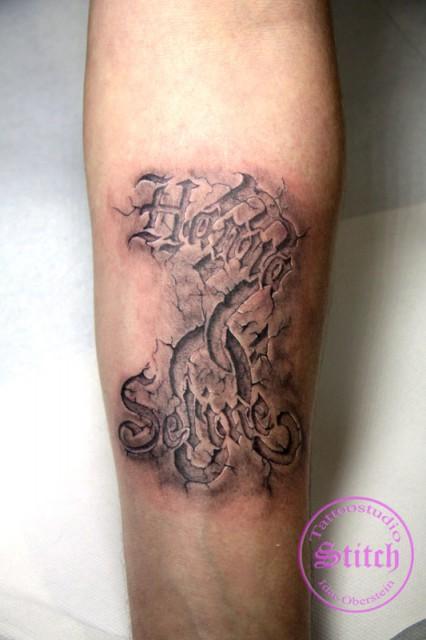
suche Schriftart eines Tattoos
hallo, suche für ein neues Tattoo für mich genau diese Schriftart der angehängten Grafik.
Kann den Künstler leider nicht mehr fragen, da er am 20.01.2020 verstorben istStitch_Idar-Oberstein_000111_25.jpg.b669d833d2317cf3729a287ee4031971.jpg
Das sind normalerweise freie Arbeiten, denen keine fertige Satzschrift zugrundeliegt. Der Künstler wird sich zwar an bestehenden Schriften orientieren, aber genau diese Formen wirst du nicht in einer Schrift finden. Ein guter und erfahrener Tätowierer kann das in diesem Stil aber selbst entwerfen.